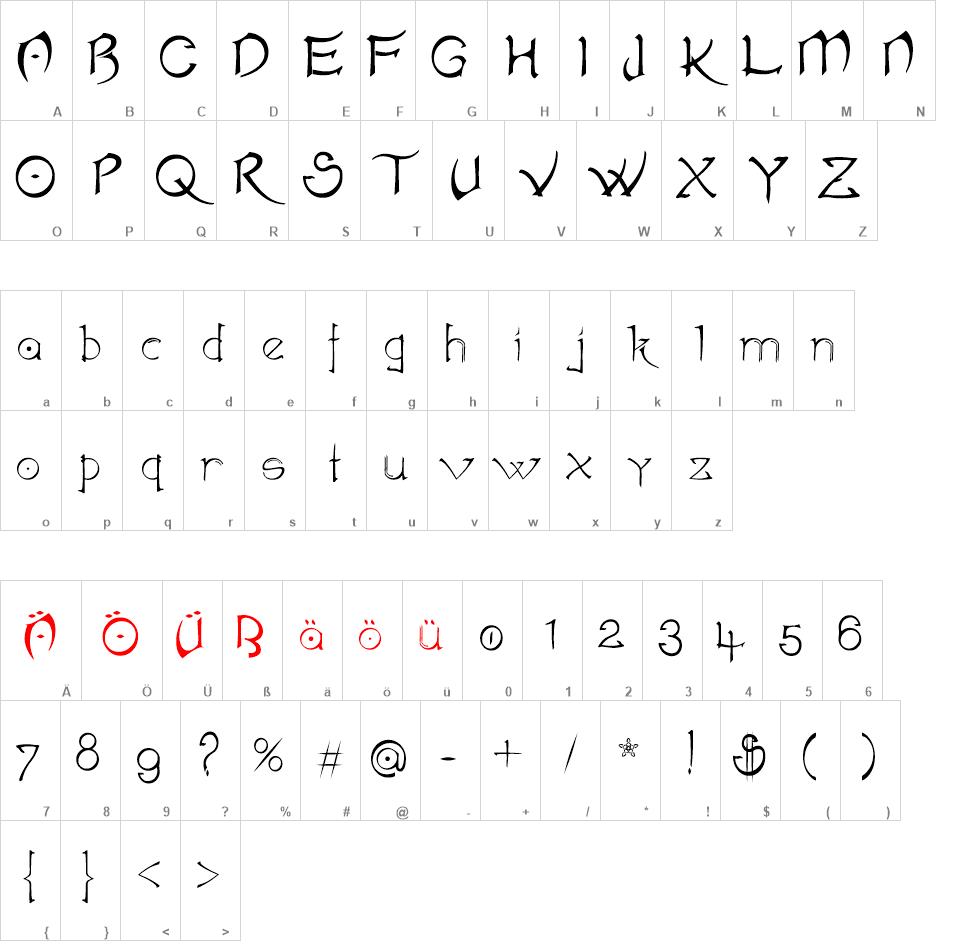
Akvaléir
Calligraphie, ethnique et délicate... Une police pour réveiller l'image du RPG.
Les capitales sont bien plus grandes par rapport aux minuscules que dans la plupart des polices. Les deux types de caractères forment d'ailleurs presque deux polices séparées. N'hésitez pas à rapetisser les capitales pour voir ce que ça donne (notez quand même que les caractères s'imbriquent correctement tels quels).